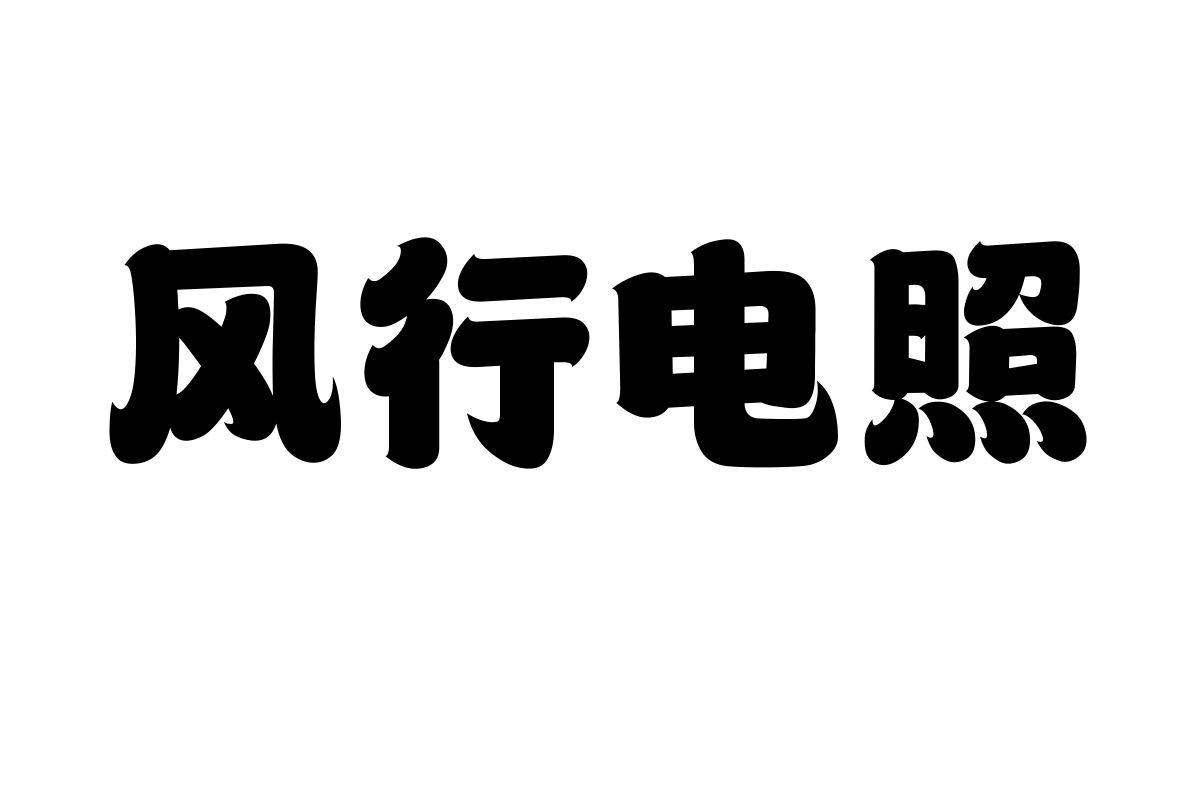
山海龙渊榜书是一种具有独特韵味和艺术价值的字体,其特点如下:
1. 字形结构:山海龙渊榜书的字形结构独特,笔画流畅自然,线条粗细有度,整体呈现出一种古朴典雅的气息。
2. 笔画特点:该字体的笔画以直线为主,线条粗犷有力,给人一种刚劲有力的感觉。同时,笔画之间的连接紧密,使得整个字体看起来更加协调统一。
3. 字体风格:山海龙渊榜书的字体风格古朴典雅,既有传统的书法韵味,又具有现代的审美观念。它既适合用于传统书法作品的创作,也适合用于现代设计中的文字排版。
4. 适用场景:山海龙渊榜书适用于各种场合的文字设计,如书籍封面、广告宣传、网页设计等。它的使用可以增加设计的层次感和艺术感,提升整体效果。
总之,山海龙渊榜书以其独特的字形结构和笔画特点,展现出一种古朴典雅的艺术风格。它既可以作为书法爱好者的创作素材,也可以作为设计师在文字设计中的选择。